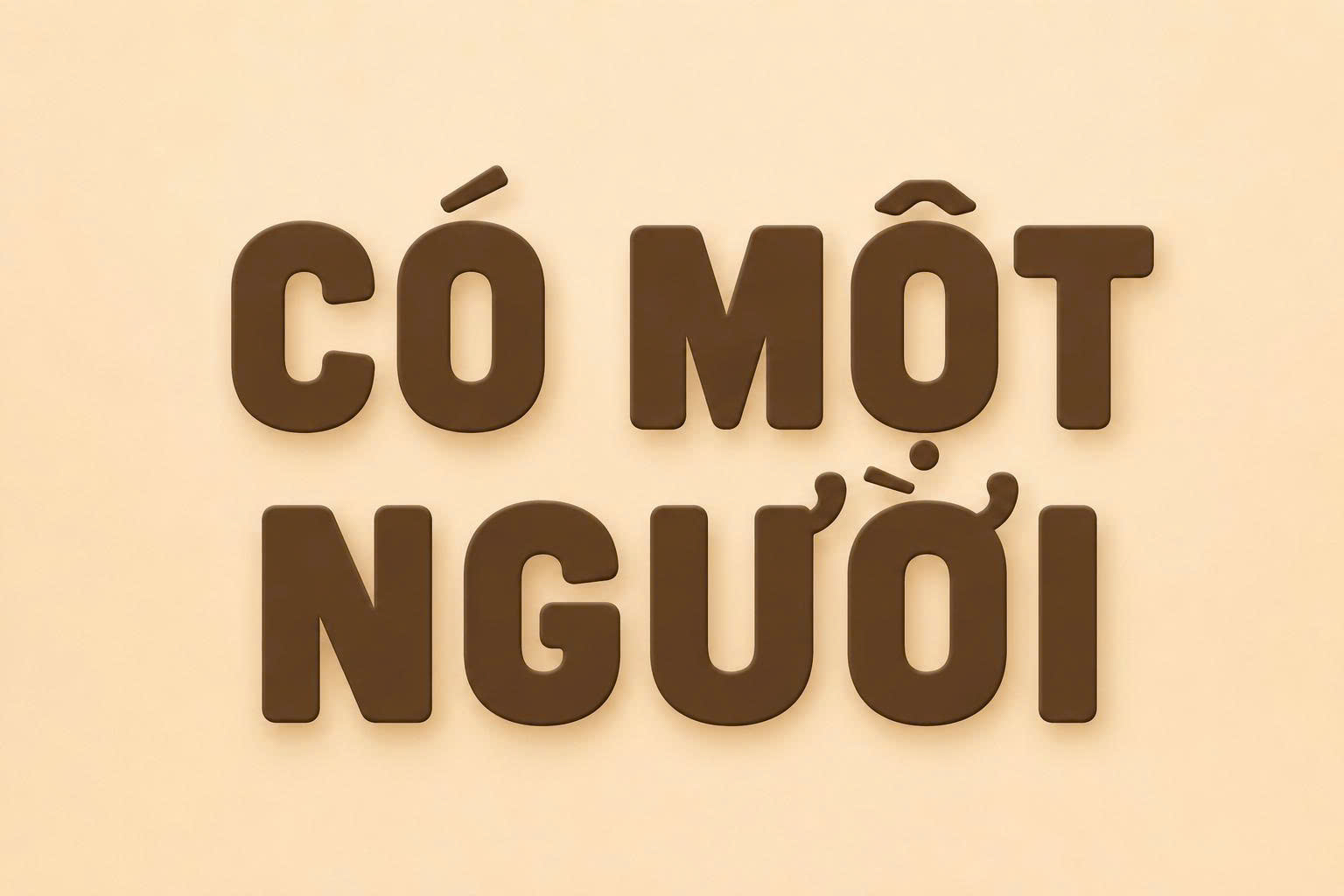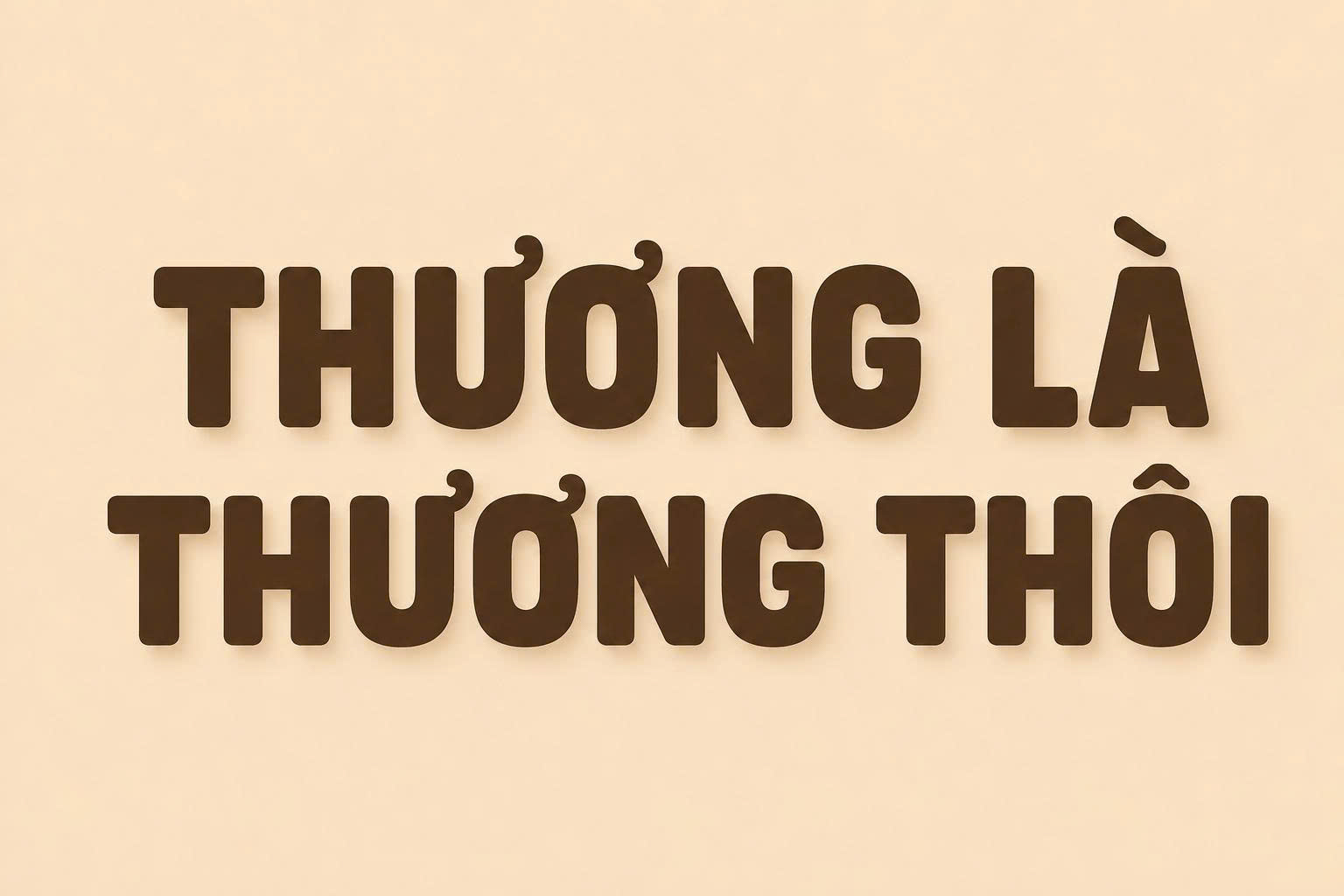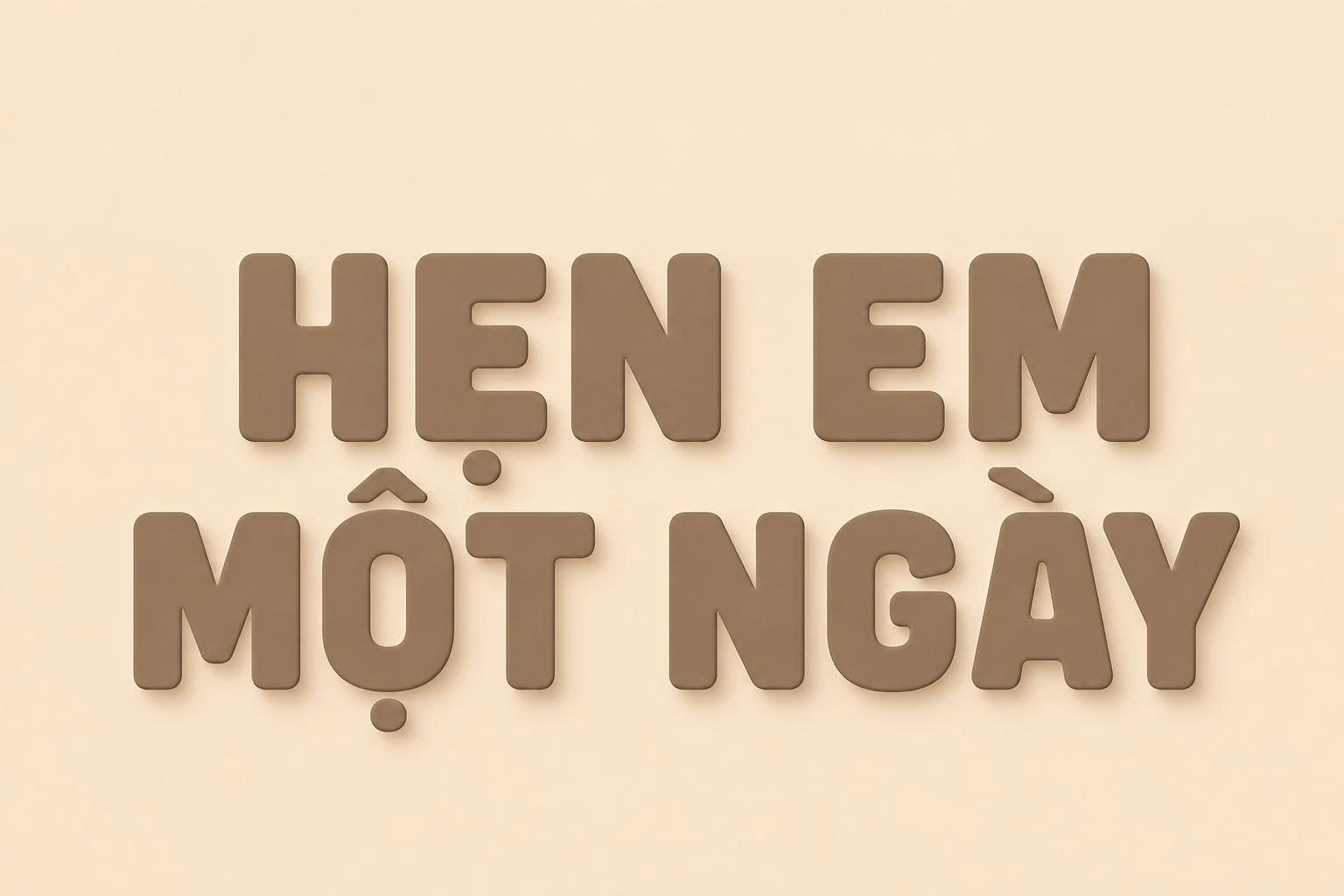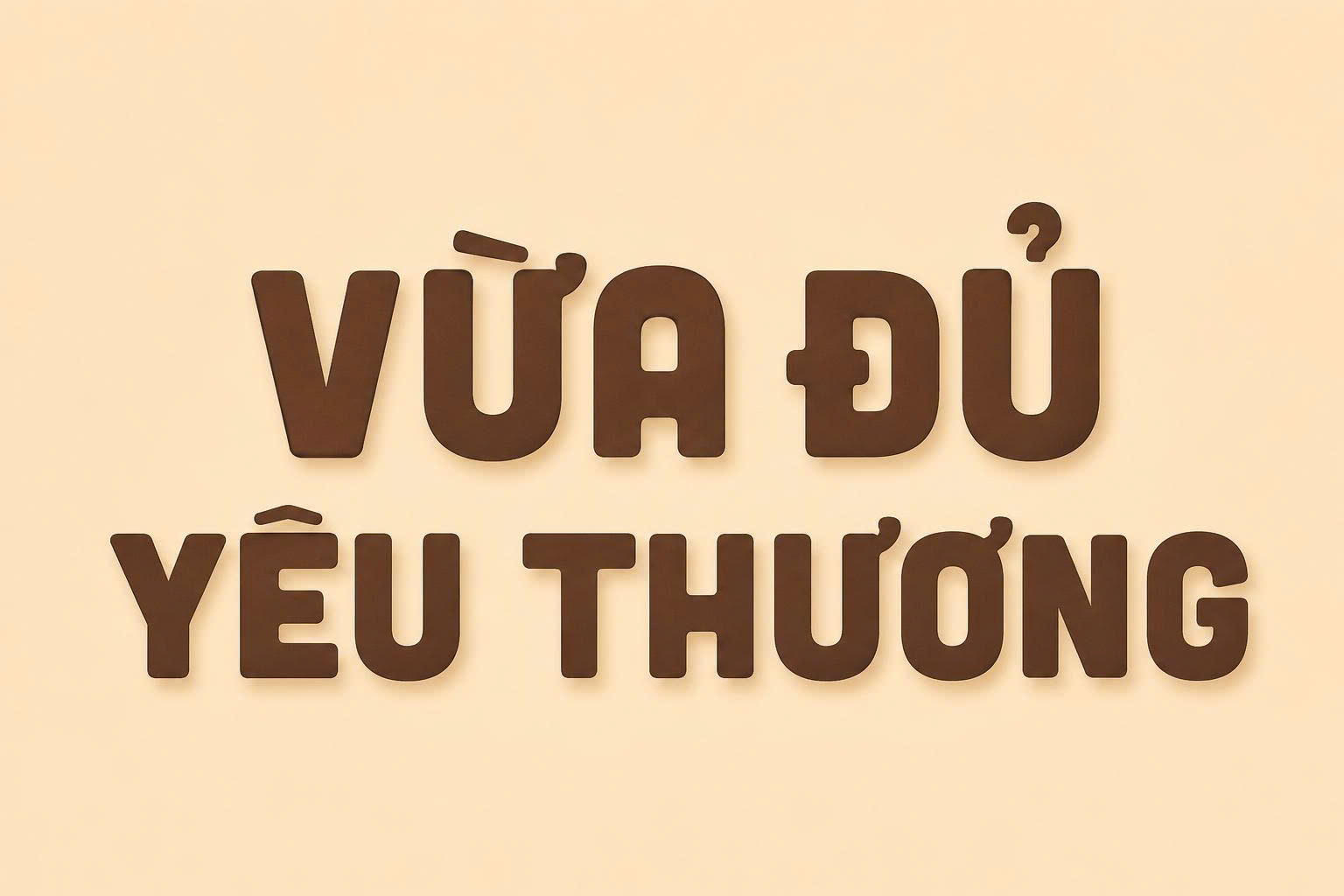
Đặc điểm thiết kế độc đáo của Font Cubano Việt hóa
Cubano mang trong mình cá tính riêng biệt, giúp bản thiết kế thoát khỏi sự khô khan của các dòng phông chữ không chân truyền thống.
Nét chữ mập mạp và vững chãi
Đặc trưng lớn nhất của font iCiel BC Cubano Normal Việt hóa là độ dày nét chữ cực kỳ lớn. Cấu trúc chữ được thiết kế theo dạng hình khối chắc chắn, mang lại cảm giác tin cậy và vững chãi. Chính đặc điểm này giúp Font Cubano hiển thị cực kỳ tốt trên các bề mặt bao bì lớn hoặc các biển hiệu quảng cáo ngoài trời.
Các góc bo tròn tạo sự thân thiện
Dù có nét chữ dày và mạnh mẽ, nhưng Cubano lại không gây cảm giác cứng nhắc nhờ kỹ thuật bo tròn các góc chữ (Rounded corners). Sự kết hợp này tạo nên một diện mạo hiện đại, trẻ trung và rất dễ tiếp cận, đặc biệt phù hợp với các thương hiệu hướng đến khách hàng trẻ hoặc ngành hàng thực phẩm, đồ uống.
- Giải quyết triệt để lỗi dấu: Bản Việt hóa từ iCiel đảm bảo các dấu thanh được đặt cân đối, không làm thay đổi chiều cao của dòng chữ, giúp bố cục thiết kế luôn chuyên nghiệp.
- Khả năng thu hút thị giác mạnh: Với độ Bold tự nhiên, font chữ này giúp tên thương hiệu trên vỏ hộp hay túi giấy nổi bật hoàn toàn mà không cần thêm quá nhiều hiệu ứng cầu kỳ.
Kinh nghiệm lựa chọn: Vì font iCiel Cubano Việt hóa có nét rất dày, khi bạn thiết kế in ấn trên chất liệu giấy có bề mặt thấm mực cao như giấy Kraft, hãy tăng nhẹ khoảng cách giữa các chữ cái (Tracking) khoảng +20 đến +50 để các khe chữ không bị bít mực sau khi in.
- Hộp thực phẩm & Đồ ăn nhanh: Nét chữ mập mạp của Cubano gợi cảm giác đầy đặn, ngon miệng, rất hợp làm tiêu đề trên hộp bánh, hộp snack.
- Tem nhãn sản phẩm: Dùng làm tên thương hiệu trên các tem nhãn decal tròn, giúp sản phẩm dễ dàng được nhận diện trên kệ hàng.
- Túi giấy thời trang: Đặc biệt là túi giấy cho các thương hiệu streetwear hoặc đồ thể thao, tạo phong cách mạnh mẽ và cá tính.